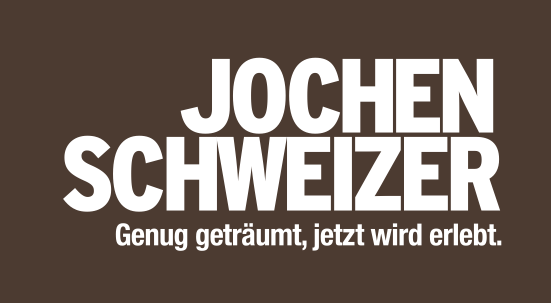
Suche diese Schrift (Jochen Schweizer)
Selber suchen? Ach so ... ja ... Suchworte ... Interstate -> FHWA-Series Schilderschrift für Highways in Gringolandia ...
Expressway, Highway Interstate ... Blue Highway ...
"Blue Highway" von Ray Larabie gibt es in einigen Schitten frei
"Highway Gothic" ist frei
"Expressway" ist kommerziell ...
"Interstate" ist kommerziell, ... siehe oben ...
"Overpass" ist SIL-OFL, also sehr frei und von Red Hat ...
Einfach mal suchen was Du an einer FHWA-D-Serie findest. Es sollte doch die D-Serie sein? Condesed -> D, Compress -> E?
Arghs! Das hätte ich nicht übersehen dürfen ... Da sind alle (?) freien Versionen drinnen: